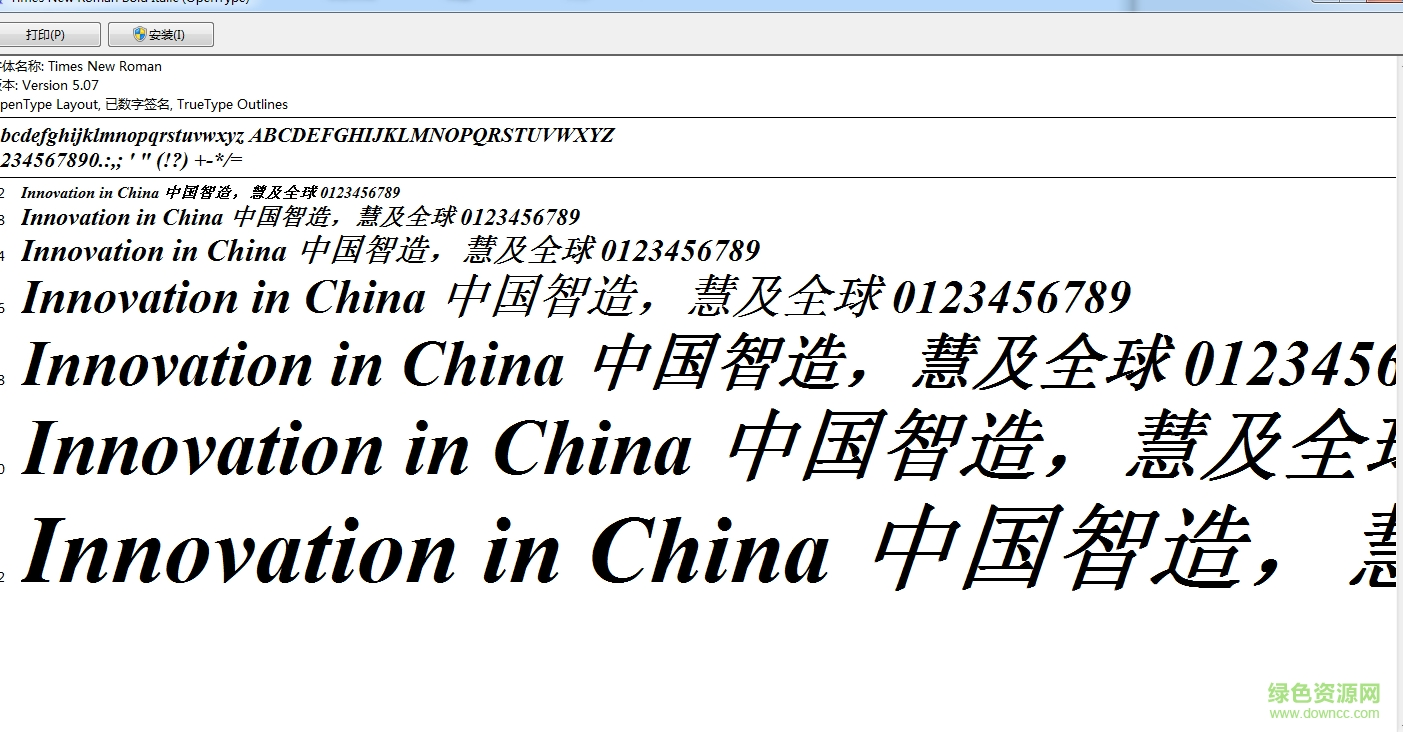
cad新羅馬字體打包
羅馬字體(Times New Roman)是word中的默認(rèn)字體,使用最廣泛、最經(jīng)典的字體非他莫屬,比一般的英文襯線字體更加舒展!需要的小伙伴快來(lái)綠色資源網(wǎng)下載吧!
新羅馬字體字體特點(diǎn):
新羅馬字體(Times New Roman)和所有襯線字體一樣,具有正統(tǒng)、規(guī)范、清晰、易辨認(rèn)的特點(diǎn),適合書(shū)籍、報(bào)紙等印刷品。
Times New Roman
Times New Roman Italic
Times New Roman Bold Italic
Times New Roman Bold